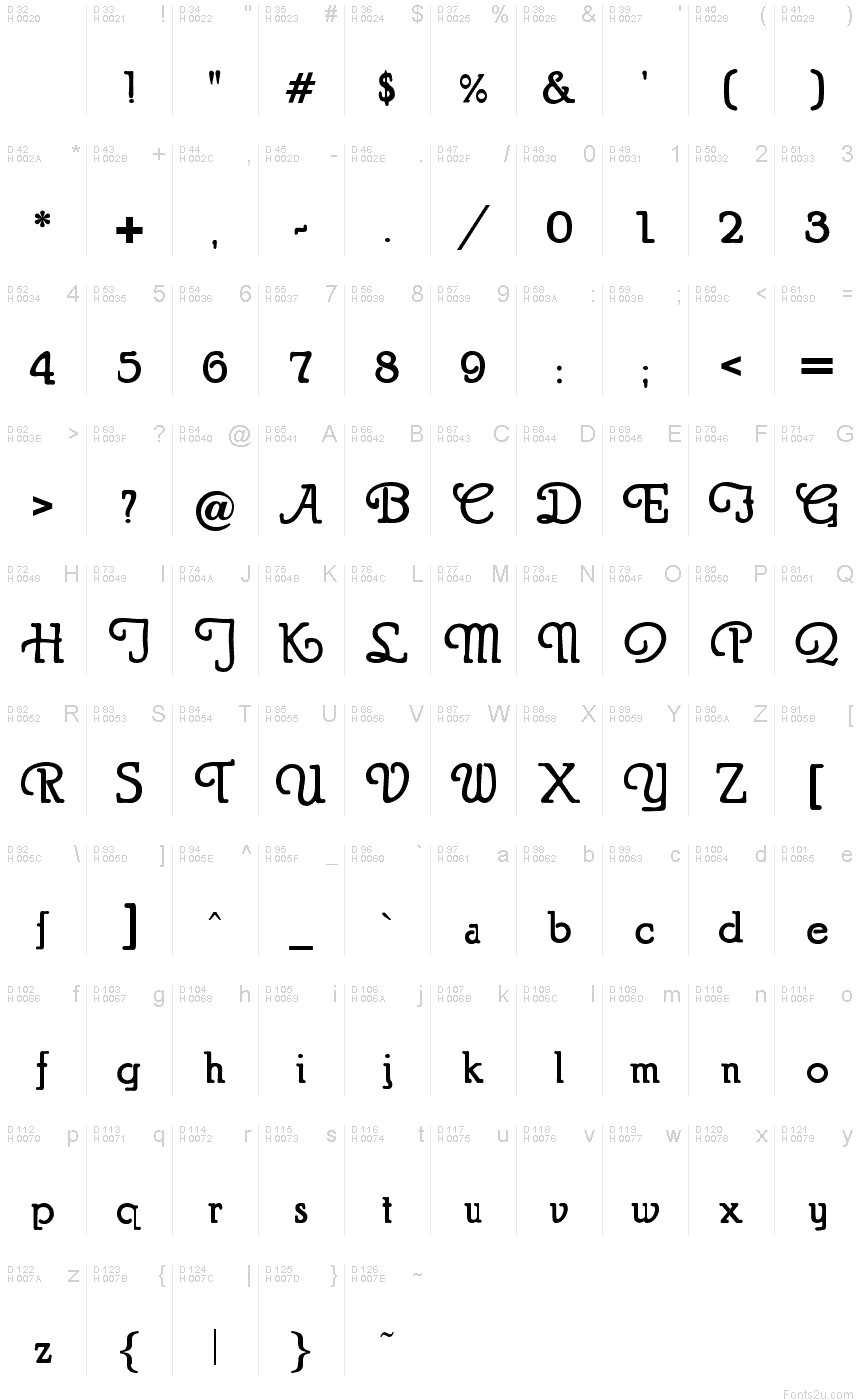
Puritan Swash Bold
Puritan Swash Bold, un font display gratuito ricco di fronzoli creato da Typographer Mediengestaltung, richiama l'atmosfera rétro delle insegne dipinte a mano grazie alle sue grandi maiuscole ricche di curve e alle minuscole rotonde, quasi piene d'inchiostro. Il suo punto di forza è il contrasto tra la generosità di quel tratto e la solidità delle lettere che seguono, che la rende ornamentale senza risultare mai troppo carica.
Questo font gratuito è perfetto per titoli di poster, branding di bar, copertine di libri, biglietti d'auguri e nomi brevi su packaging, dove un'iniziale decorativa è in grado di definire l'intera riga. Dà il meglio di sé in contesti brevi, specialmente nei titoli o nelle copertine, perché la maiuscola avvolgente crea subito un punto focale immediato, mentre il resto della parola mantiene un aspetto caldo e solido.